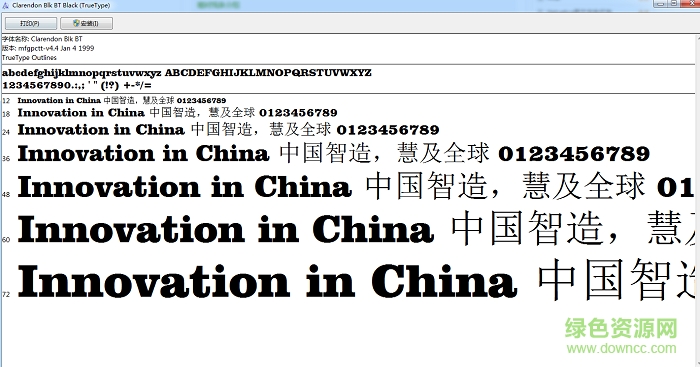
clarendon blk bt
clarendon blk bt字體是一款精致好看的襯線字體,筆劃棱角分明,有粗有細(xì),易于閱讀,常常用于各類印刷品,需要這款字體的小伙伴趕緊來綠色資源網(wǎng)下載吧!
英文襯線字體分類
1.具有特定曲線襯線的「支架襯線體」(bracket serif)
2.連接處為細(xì)直線的「發(fā)絲襯線體」(hairline serif)
3.厚粗四角形的「板狀襯線體」(slab serif)
clarendon blk bt